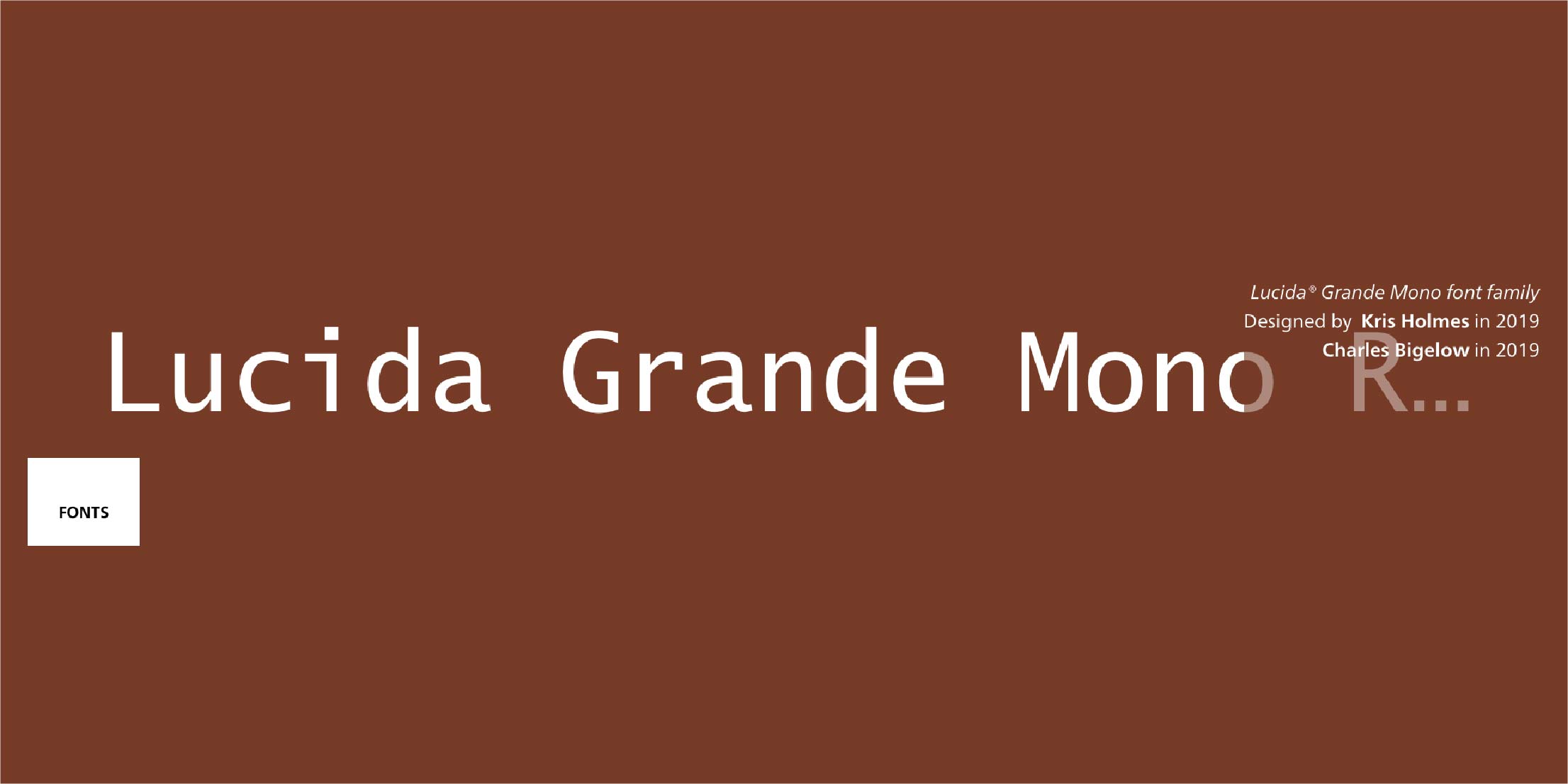
Lucida® Grande Mono
字体品牌: Monotype 设计师:Holmes,Kris,Bigelow,Charles 字体分类:无衬线体 字体属性:外文 字符集:Unicode 发布时间: 2019
Lucida Grande Mono 是一款具有人文主义风格的无衬线字体,具有较大的 X 高度,字体清晰,字距适宜,易读性高,小字号在打印和屏幕显示环境下同样清晰。
Lucida Grande Mono 的字重、比例和外观都与 Lucida grande 相匹配,但字母等宽,使其在实际应用中广受欢迎,在编程,终端仿真、打字机、商业或个人信件领域均有不错的表现。
W1G 字符集包括拉丁、希腊和西里尔字母,支持欧洲、美洲和世界各地的许多语言。